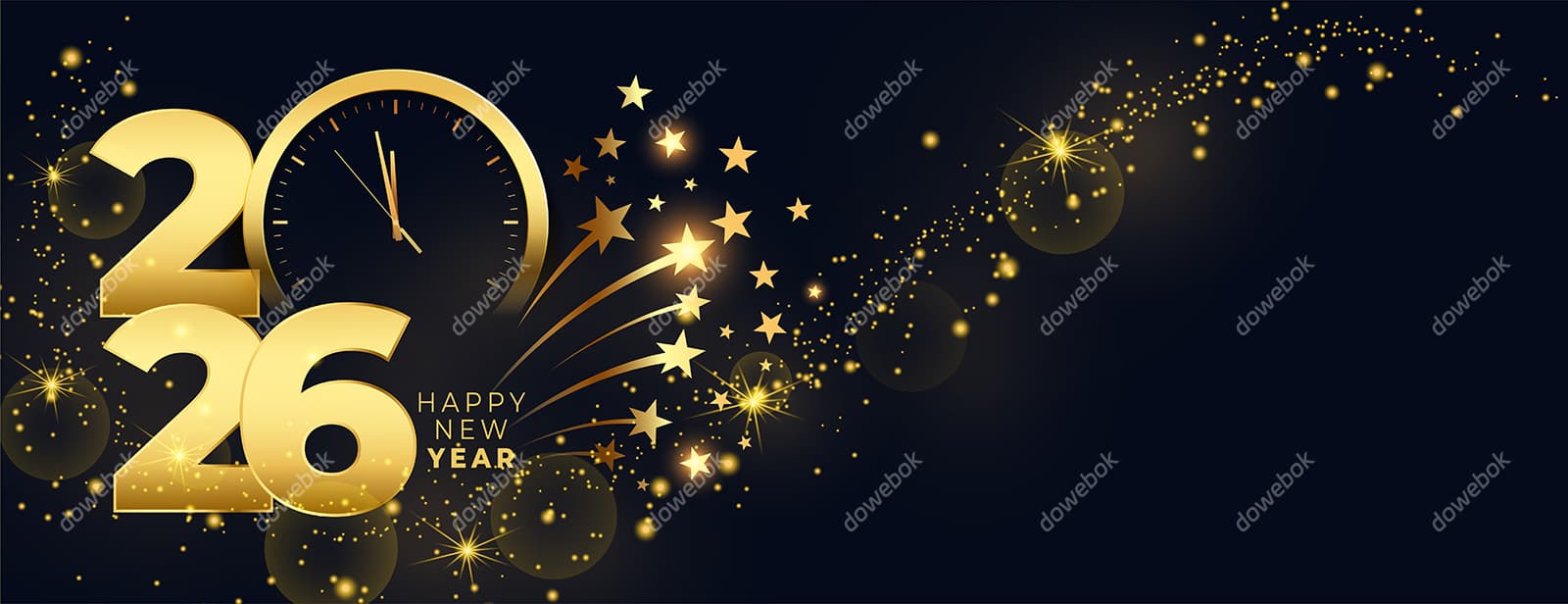
这是一款金色时钟和数字设计的 2026 新年快乐矢量素材,深黑背景缀满金星光斑,鎏金 “2026” 字体中嵌着时钟元素,契合跨年倒计时的氛围,旁侧金星与烟火状光斑更添热烈感,“HAPPY NEW YEAR” 字样点缀其间。整体以黑金配色融合计时符号与闪耀细节,既显跨年的盛大仪式感,又用星光元素烘托出欢庆的节日张力,精致且富有动感。